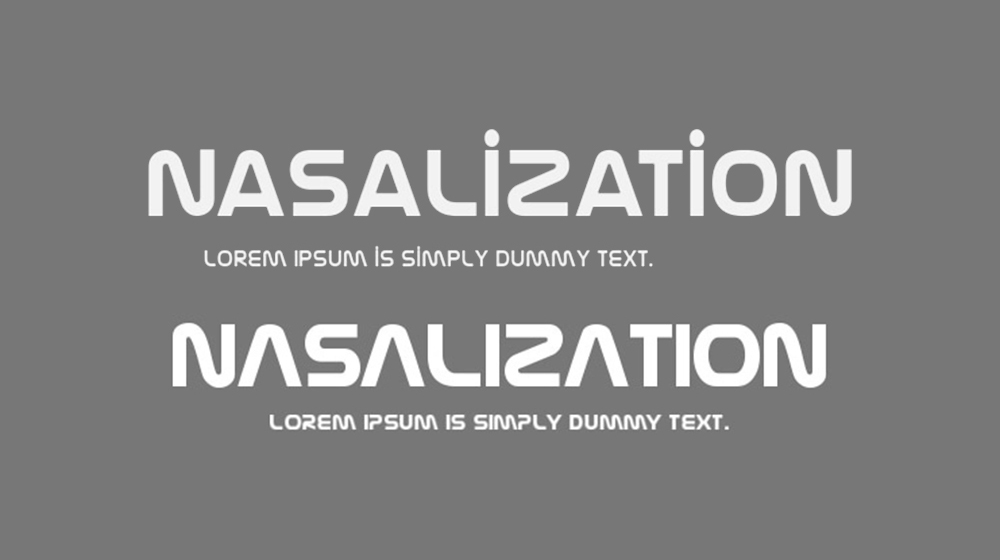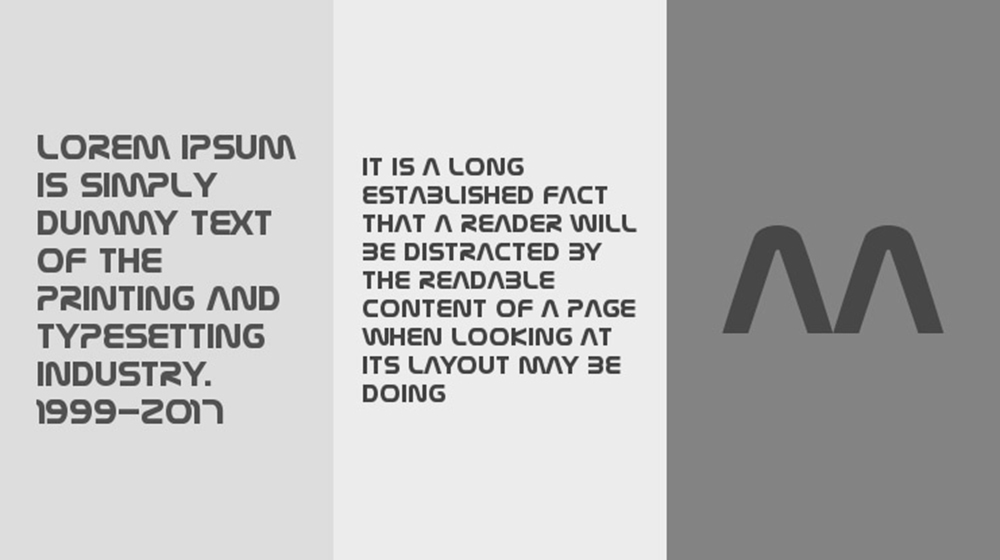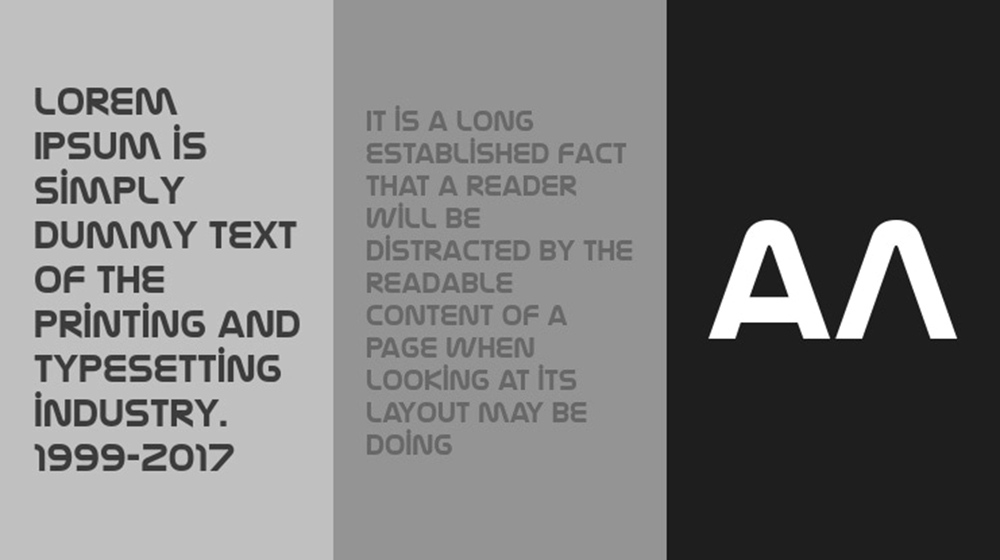
فونت پرمیوم و انگلیسی Nasalization Font یک فونت نمایشی تکنو سان سریف فوق مدرن با اشارهای به لوگوی ناسا در سال ۱۹۷۵ است. در برنامههای هوشمند OpenType، یک M و W با شیب، بسته به کاراکتر قبل یا بعد از خود، به جهت دیگر حرکت میکنند یا مستقیم میشوند. خط متقاطع را میتوان با کمک جایگزینهای سبکی OpenType اضافه کرد.